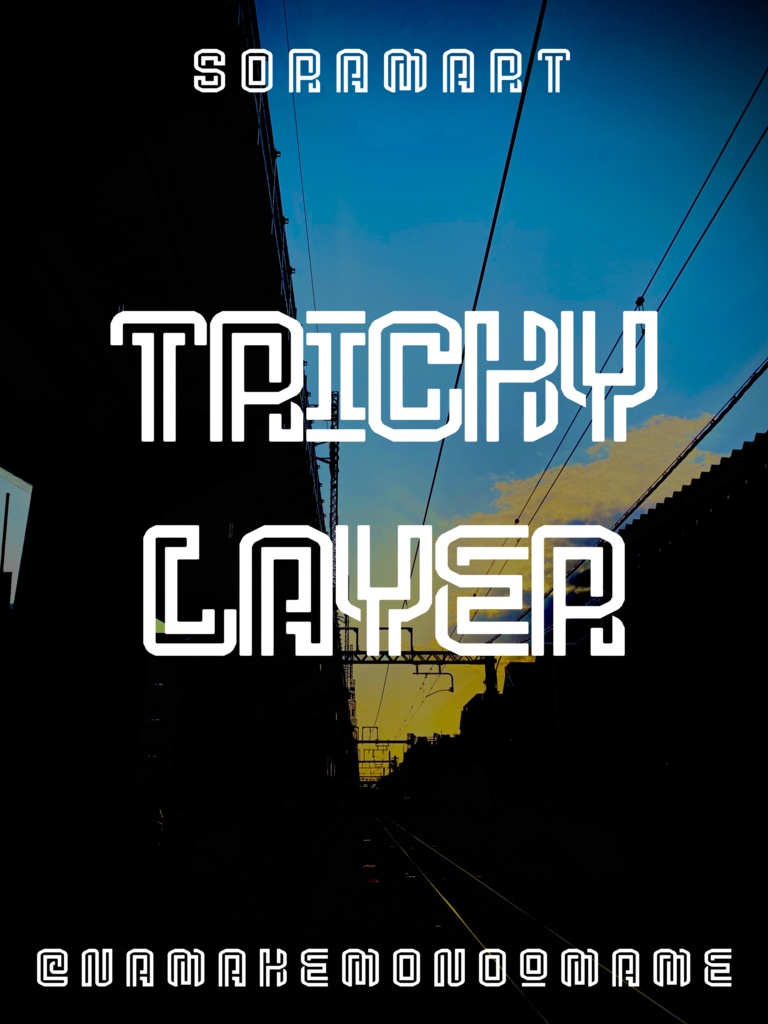
そらマートフォントデータ”Tricky Layer”Digital2,500 JPY加入购物车Buy a GiftAbout Gift二層構造になった2つのラインが入り組むフォント "Tricky Layer" です。 「TrueTypeフォントファイル」という形式です。 ダウンロードした後、Zipファイル内のデータをインストールしてお使いください。 このフォントは商用利用可となっております。 お客様の制作・創作活動のお役に立てれば幸いです。 ※使用上の注意事項などは、添付のReadmeをお読みください。そらマートVisit FANBOX!Fontsフォントデータ”Longtail Sans Serif Slashed”そらマート2,500 JPYFontsフォントデータ”Longtail Sans Serif Bold”そらマート0 JPYFontsフォントデータ”Longtail Sans Serif”そらマート0 JPYFontsフォントデータ”Pretty Commando”そらマート2,500 JPYFontsフォントデータ”Abyss Dive Punk Retro”そらマート2,500 JPYFontsフォントデータ”Abyss Dive Punk Wide”そらマート2,500 JPYFontsフォントデータ”Abyss Dive Punk”そらマート2,500 JPYFontsフォントデータ”Emerald Sphere Sprite”そらマート2,500 JPYFontsフォントデータ”Emerald Sphere Long”そらマート2,500 JPYFontsフォントデータ”Emerald Sphere”そらマート2,500 JPYFontsフォントデータ”Monolith Glitch”そらマート2,500 JPYFontsフォントデータ”Monolith Formula”そらマート2,500 JPYFontsフォントデータ”Rolling Cute”そらマート2,500 JPYFontsフォントデータ”Tricky Wire Merge”そらマート2,500 JPYFontsフォントデータ”Tricky Layer Wide”そらマート2,500 JPYFontsフォントデータ”Popcorn Tab Plasma”そらマート2,500 JPYFontsフォントデータ”Popcorn Tab Heavy”そらマート2,500 JPYFontsフォントデータ”Popcorn Tab”そらマート2,500 JPYFontsフォントデータ”Tetra Pixel Dash”そらマート2,500 JPYFontsフォントデータ”Tetra Pixel Fluid”そらマート2,500 JPY查看更多